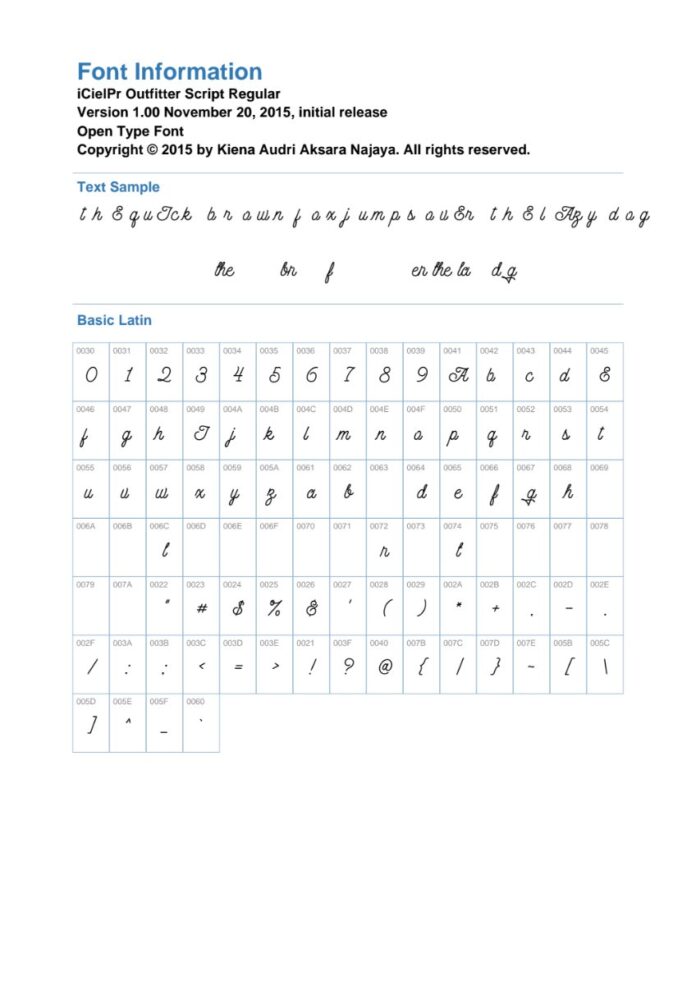
Font Outfitter Script Đẹp
Font Outfitter Script Đẹp. Font Outfitter Script là một lựa chọn tuyệt vời cho những ai tìm kiếm sự tinh tế và cá nhân hóa trong thiết kế. Với phong cách viết tay mềm mại, font này mang đến vẻ đẹp độc đáo, phù hợp cho nhiều dự án sáng tạo, từ thiệp mời đến logo.
Trong thế giới thiết kế đồ họa, việc lựa chọn font chữ phù hợp có thể tạo nên sự khác biệt lớn cho tác phẩm của bạn. Font Outfitter Script là một trong những lựa chọn nổi bật, mang đến vẻ đẹp tinh tế, mềm mại và đầy cá tính. Được phát hành lần đầu vào ngày 20 tháng 11 năm 2015 bởi Klena Audri Aksara Najaya, Outfitter Script nhanh chóng trở thành một font chữ được yêu thích bởi các nhà thiết kế trên toàn thế giới.
Giới thiệu về Font Outfitter Script
Outfitter Script là một font chữ script (viết tay) thuộc loại OpenType Font. Đặc trưng của font này là các nét chữ mềm mại, uyển chuyển, mô phỏng chân thực nét viết tay của con người. Điều này tạo nên một cảm giác gần gũi, thân thiện nhưng không kém phần sang trọng và chuyên nghiệp. Với phiên bản 1.00, font đã cung cấp đầy đủ các ký tự cơ bản của bảng chữ cái Latin, số và các ký tự đặc biệt, đáp ứng đa dạng nhu cầu sử dụng.
Sự ra đời của Outfitter Script đã mang đến một làn gió mới cho các dự án thiết kế, đặc biệt là những dự án cần sự cá nhân hóa cao. Từ thiệp cưới, thiệp mời sinh nhật, logo thương hiệu, cho đến các ấn phẩm quảng cáo cao cấp, font chữ này đều có thể phát huy tối đa vẻ đẹp của mình.
Đặc điểm nổi bật của Font Outfitter Script
• Phong cách viết tay tự nhiên: Các nét chữ được thiết kế tỉ mỉ, mô phỏng chân thực nét viết tay, tạo cảm giác mềm mại, uyển chuyển và rất tự nhiên.
• Tính linh hoạt cao: Phù hợp với nhiều loại hình thiết kế khác nhau, từ in ấn đến kỹ thuật số.
• Dễ đọc: Mặc dù là font script, Outfitter Script vẫn đảm bảo tính dễ đọc, không gây khó khăn cho người xem.
• Hỗ trợ đa ngôn ngữ: Với bộ ký tự Latin cơ bản, font có thể được sử dụng rộng rãi trong nhiều ngôn ngữ.
Ứng dụng của Font Outfitter Script trong thiết kế
Với vẻ đẹp độc đáo của mình, Font Outfitter Script có thể được ứng dụng trong rất nhiều lĩnh vực:
Thiết kế logo và nhận diện thương hiệu
Đối với các thương hiệu muốn thể hiện sự tinh tế, sang trọng và cá nhân hóa, Outfitter Script là một lựa chọn lý tưởng. Font chữ này có thể giúp tạo ra những logo độc đáo, dễ nhớ và mang đậm dấu ấn riêng. Ví dụ, các cửa hàng thời trang cao cấp, tiệm bánh thủ công, studio ảnh cưới thường rất ưa chuộng phong cách này.
Thiết kế thiệp mời và thiệp chúc mừng
Sự mềm mại và lãng mạn của Outfitter Script rất phù hợp để thiết kế thiệp cưới, thiệp sinh nhật, thiệp chúc mừng các dịp lễ. Font chữ này sẽ làm cho những thông điệp trở nên ý nghĩa và ấm áp hơn, tạo ấn tượng sâu sắc cho người nhận.
Thiết kế bao bì sản phẩm
Đối với các sản phẩm thủ công, sản phẩm organic hoặc các sản phẩm cao cấp, việc sử dụng Outfitter Script trên bao bì có thể tăng thêm giá trị thẩm mỹ và sự độc đáo. Nó giúp sản phẩm nổi bật hơn trên kệ hàng và thu hút sự chú ý của khách hàng.
Thiết kế website và blog
Trong thiết kế web, Outfitter Script có thể được sử dụng cho tiêu đề, slogan hoặc các đoạn văn bản ngắn để tạo điểm nhấn. Nó giúp website trở nên thân thiện, cá tính và chuyên nghiệp hơn, đặc biệt là các blog về phong cách sống, ẩm thực, thời trang.
Thiết kế ấn phẩm quảng cáo
Từ poster, banner, brochure cho đến các bài đăng trên mạng xã hội, Outfitter Script đều có thể được sử dụng để tạo ra những ấn phẩm quảng cáo đẹp mắt và thu hút. Nó giúp thông điệp truyền tải một cách hiệu quả và ấn tượng.
Cách sử dụng Font Outfitter Script hiệu quả
Để phát huy tối đa vẻ đẹp của Font Outfitter Script, bạn cần lưu ý một số điểm sau:
• Kết hợp với font chữ khác: Outfitter Script thường đẹp nhất khi được sử dụng làm tiêu đề hoặc điểm nhấn. Bạn nên kết hợp nó với một font chữ sans-serif hoặc serif đơn giản, dễ đọc cho phần nội dung chính để tạo sự cân bằng và hài hòa.
• Kích thước phù hợp: Do đặc trưng là font script, Outfitter Script thường cần kích thước lớn hơn một chút để đảm bảo tính dễ đọc, đặc biệt là khi sử dụng cho các đoạn văn bản dài.
• Khoảng cách chữ (kerning) và dòng (leading): Điều chỉnh kerning và leading một cách hợp lý sẽ giúp font chữ trông gọn gàng và chuyên nghiệp hơn.
• Màu sắc: Lựa chọn màu sắc phù hợp sẽ làm nổi bật vẻ đẹp của font. Các màu sắc pastel, màu vàng đồng, hoặc màu đen trắng thường rất hợp với phong cách này.
Font này rất phù hợp cho thiết kế logo, nhận diện thương hiệu, thiệp mời, thiệp chúc mừng, bao bì sản phẩm, website, blog và các ấn phẩm quảng cáo cần sự mềm mại, sang trọng và cá nhân hóa.
Làm thế nào để sử dụng Font Outfitter Script hiệu quả?
Để sử dụng hiệu quả, bạn nên kết hợp nó với các font chữ đơn giản khác, chọn kích thước phù hợp, điều chỉnh khoảng cách chữ và dòng, và lựa chọn màu sắc hài hòa để làm nổi bật vẻ đẹp của font.